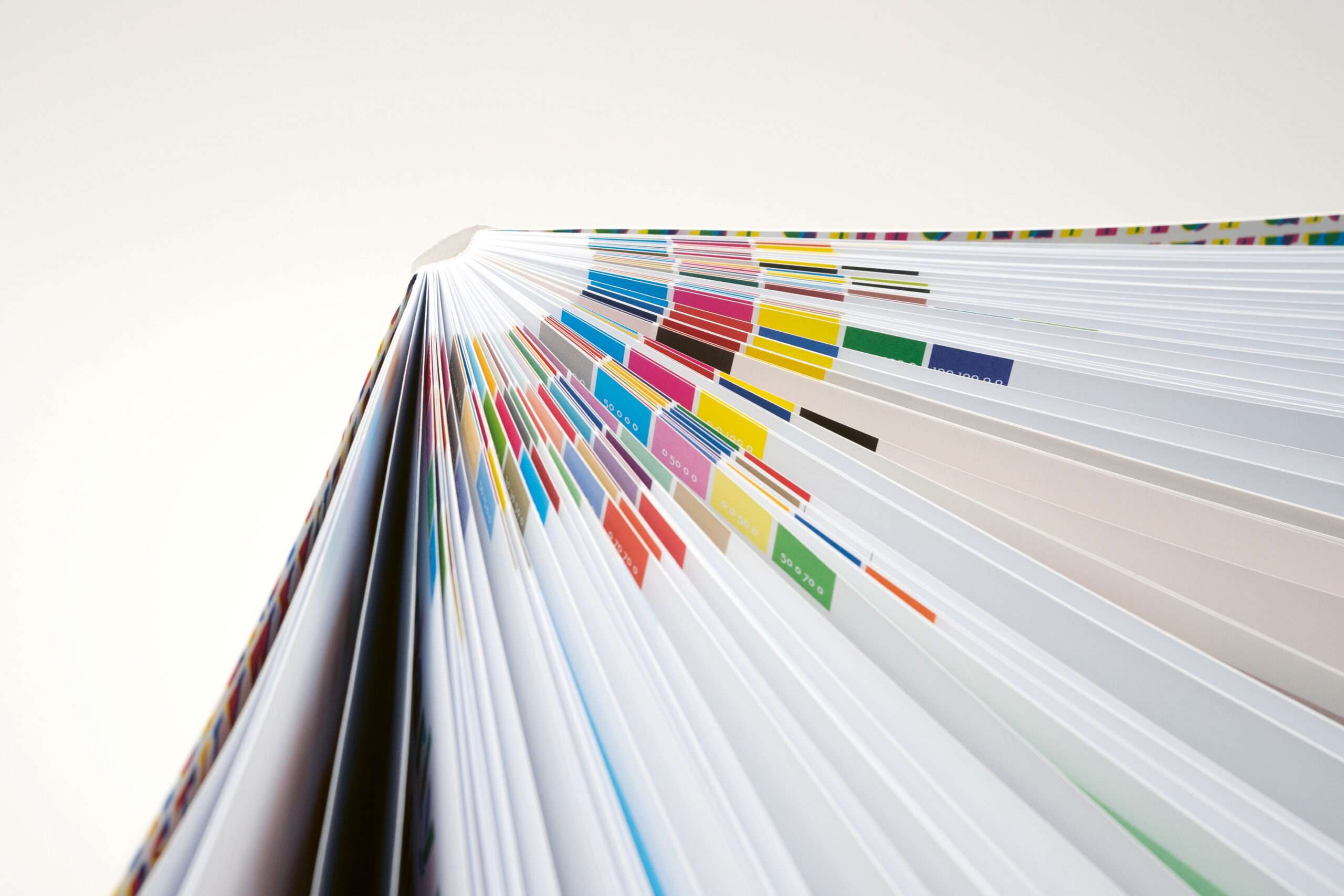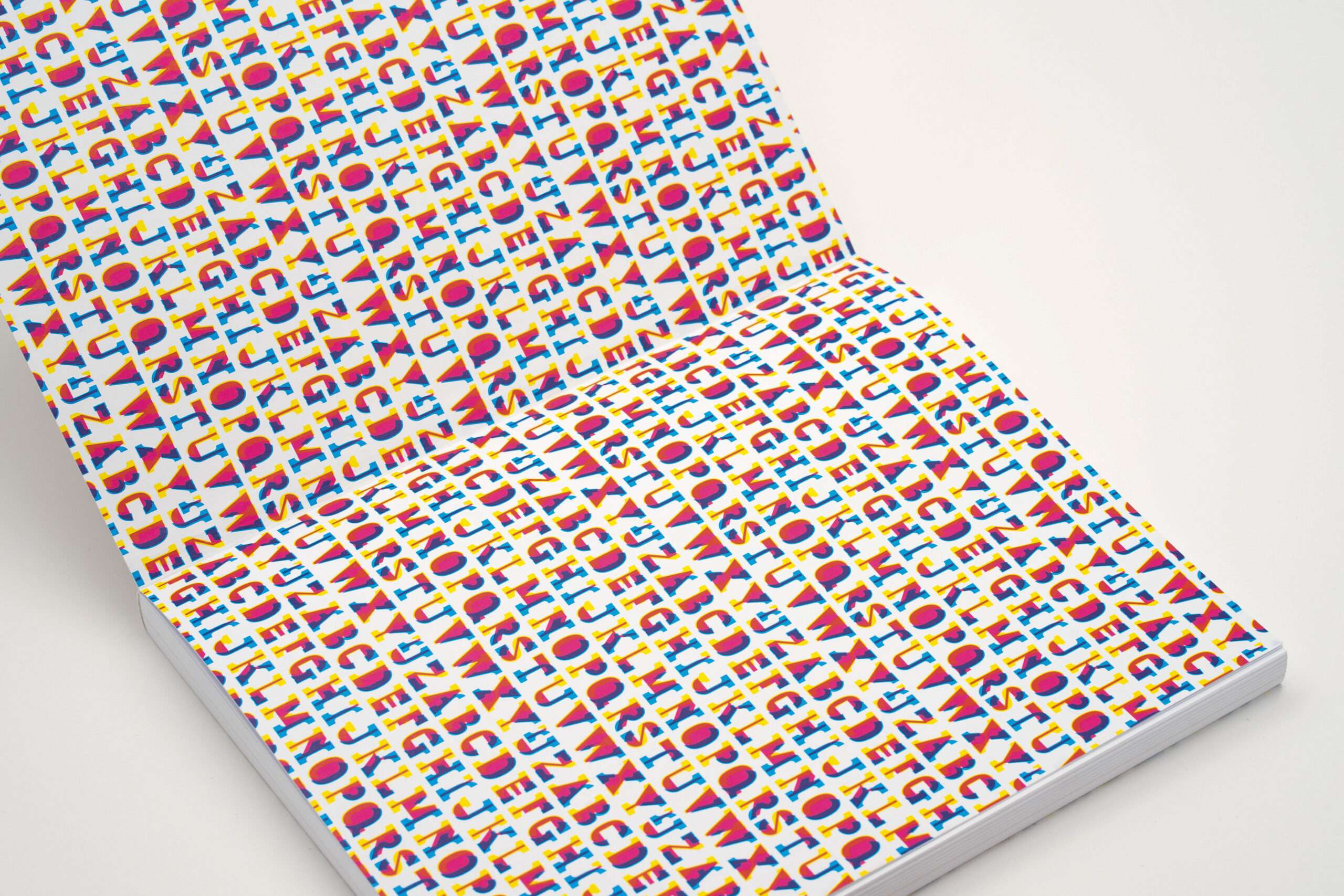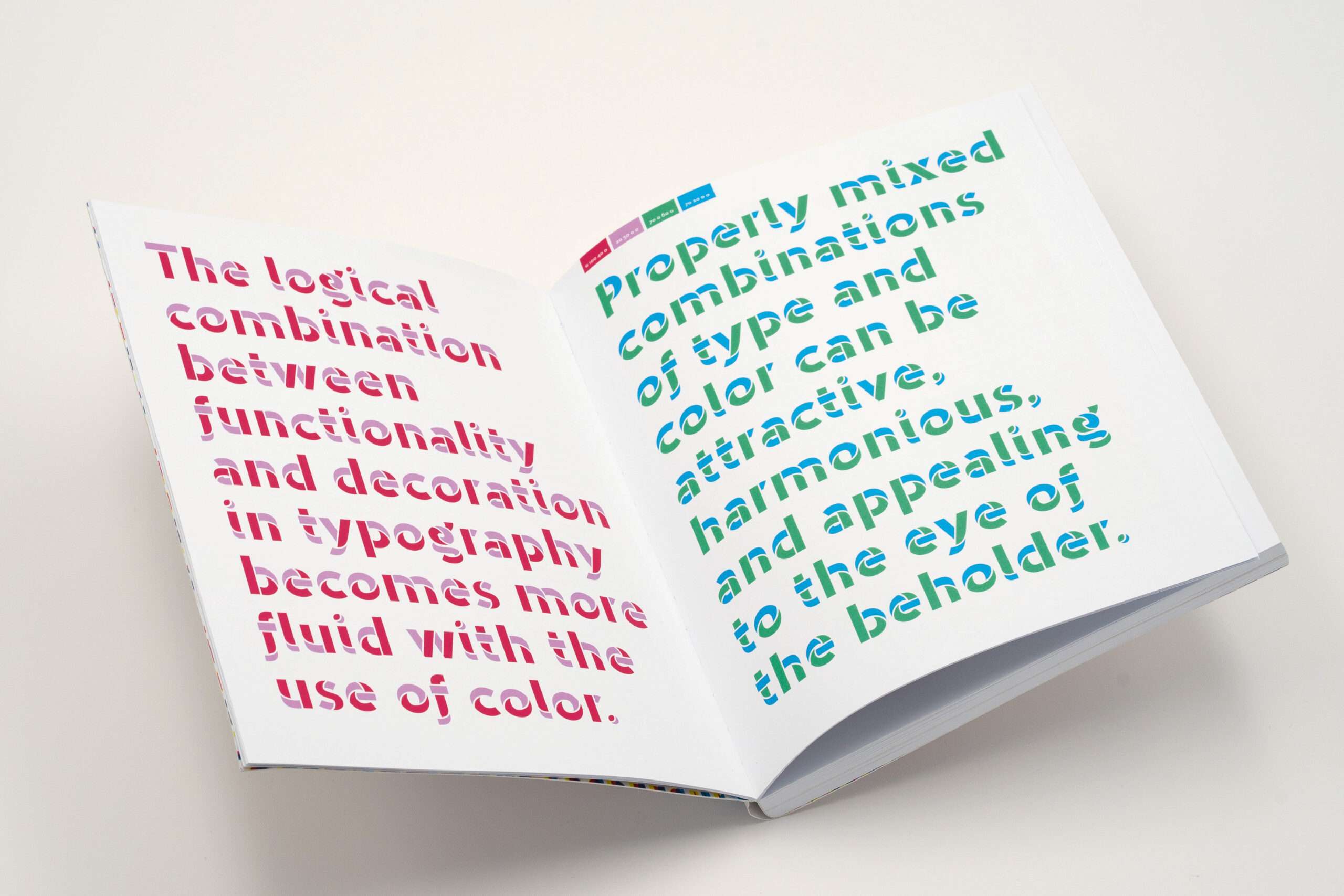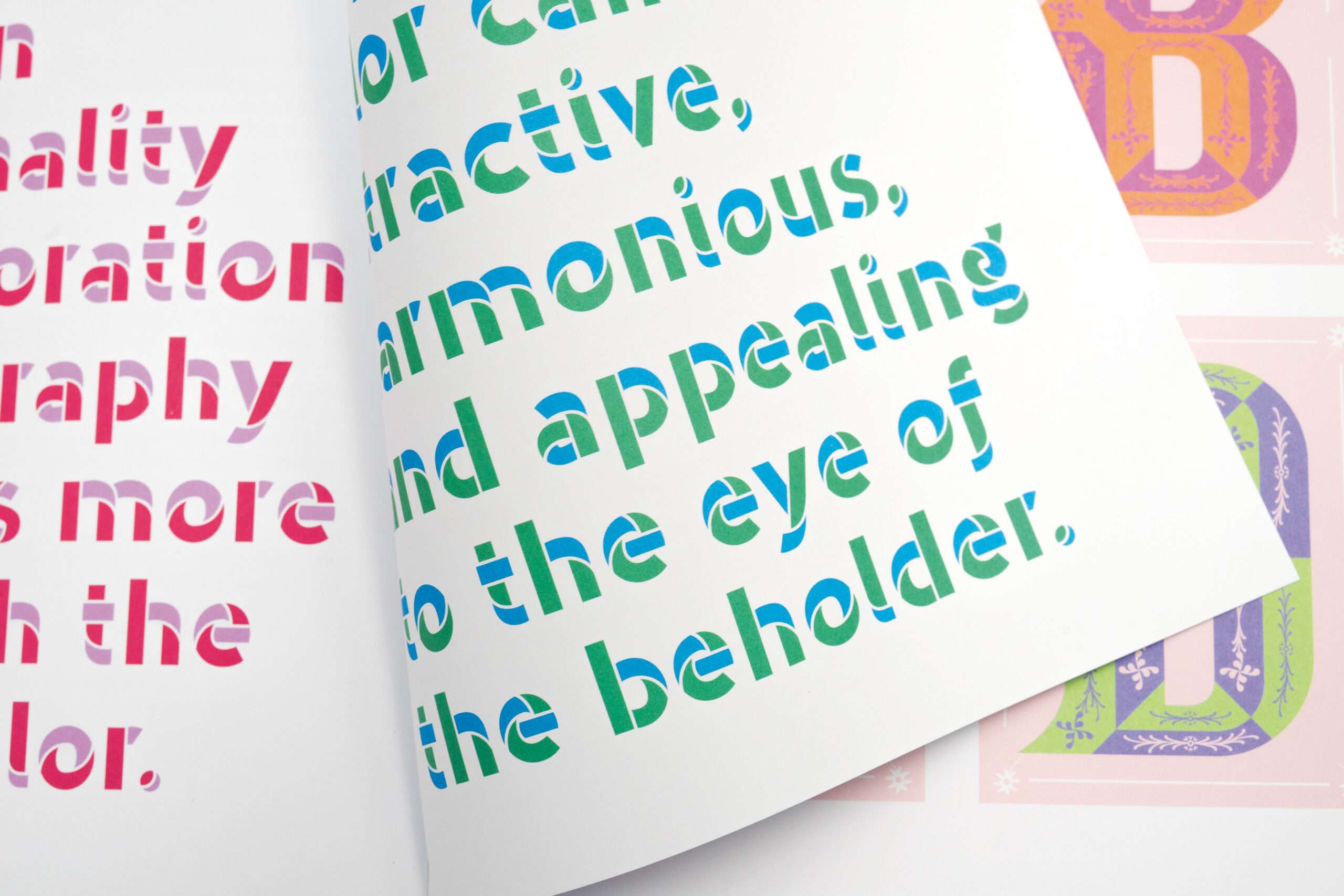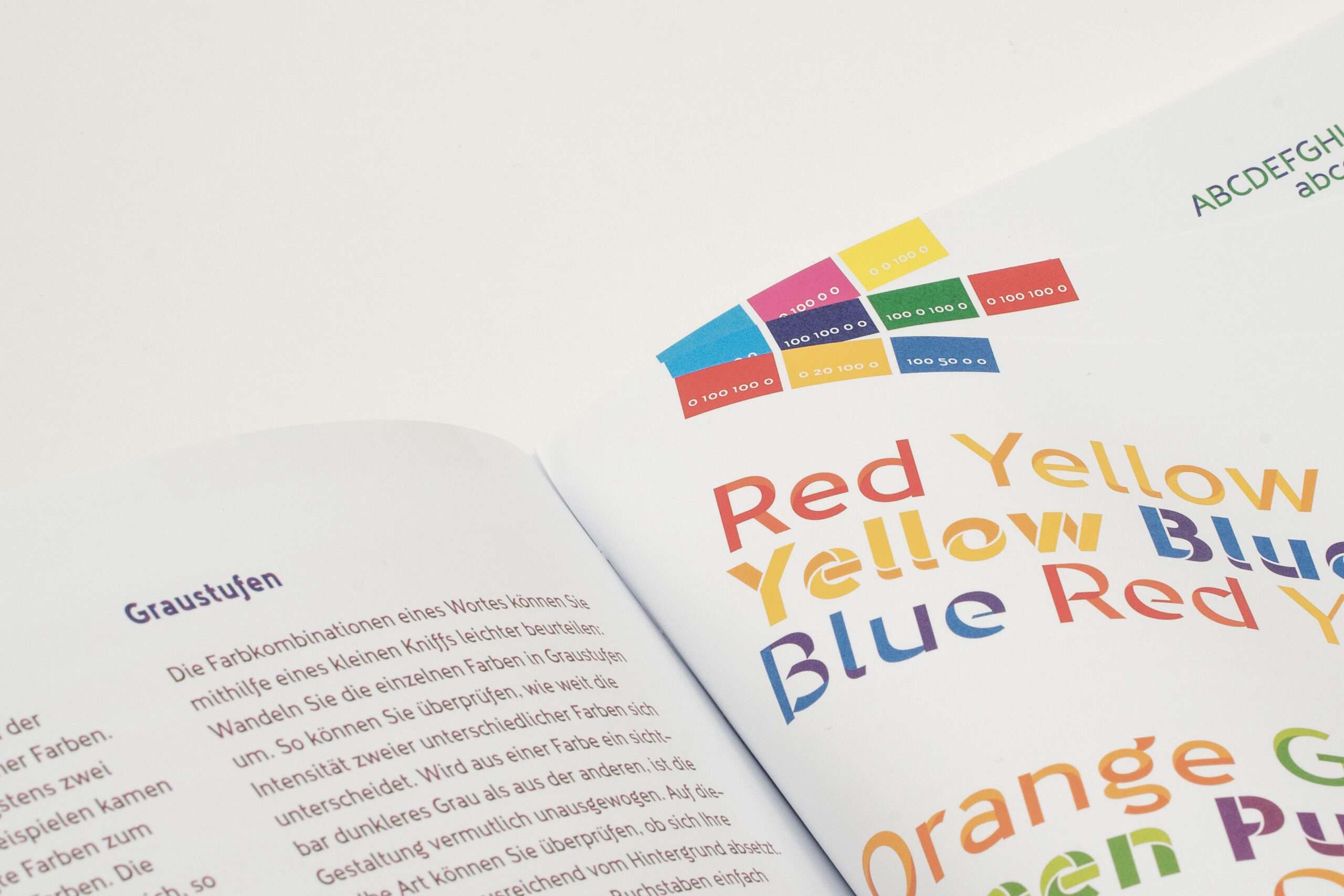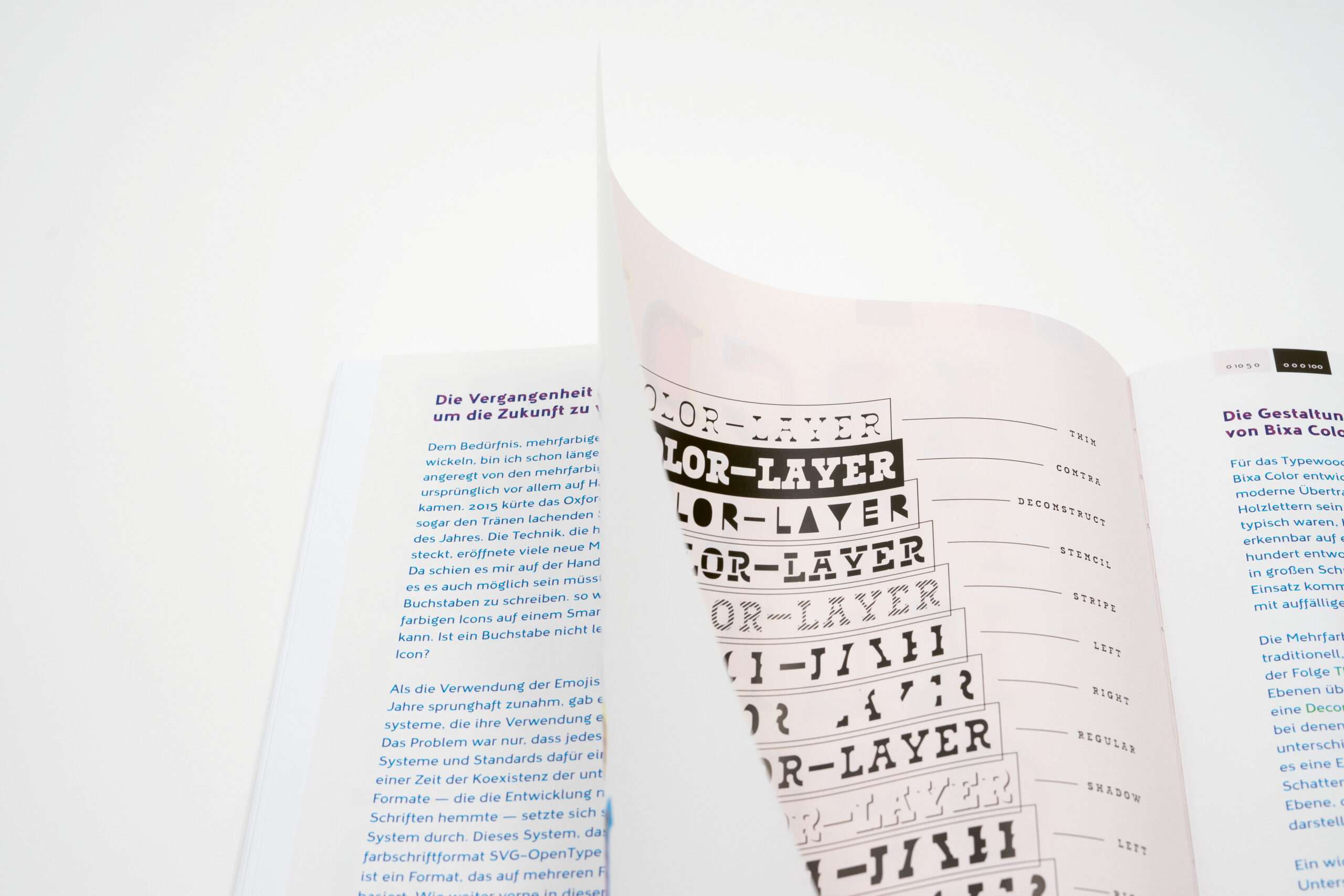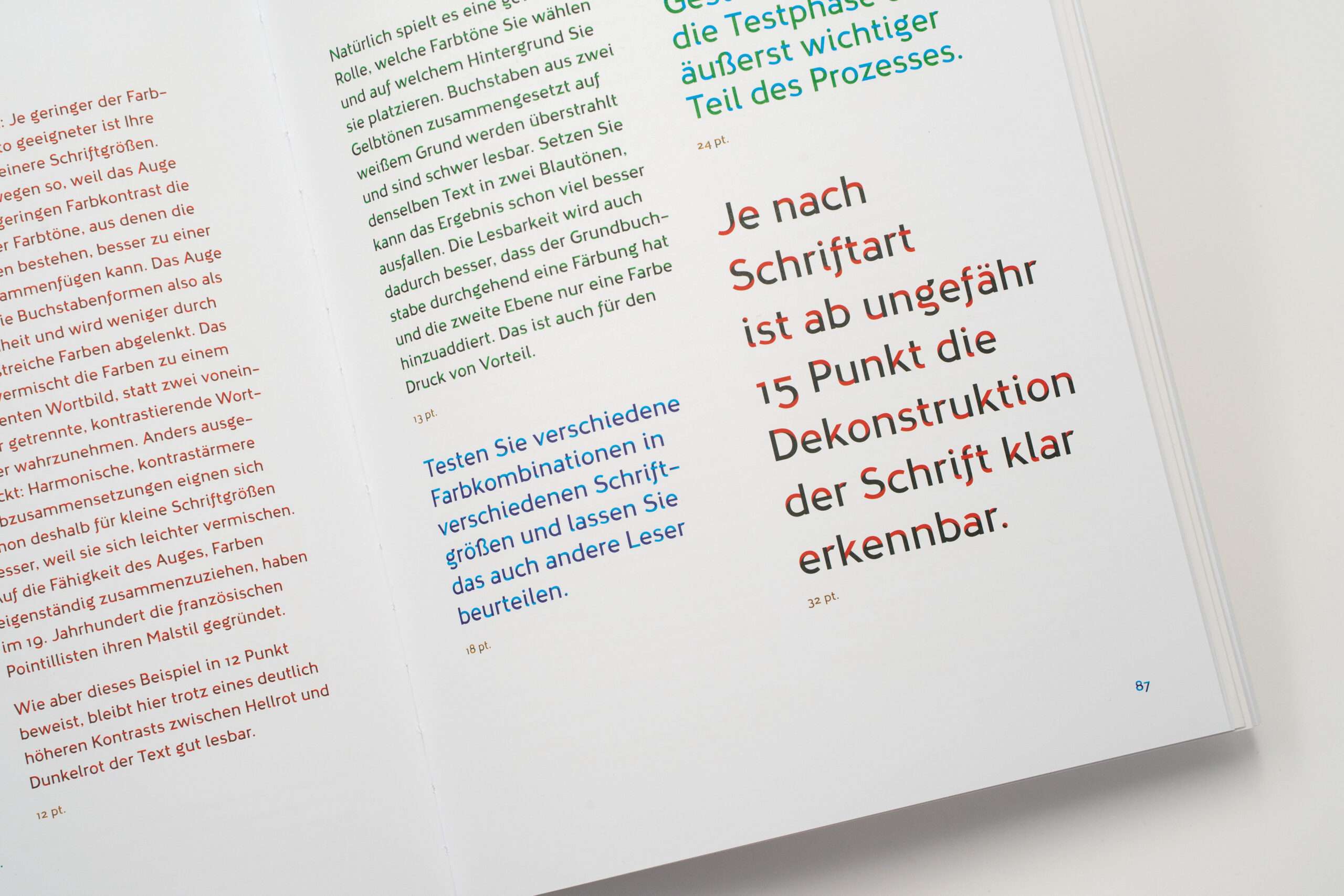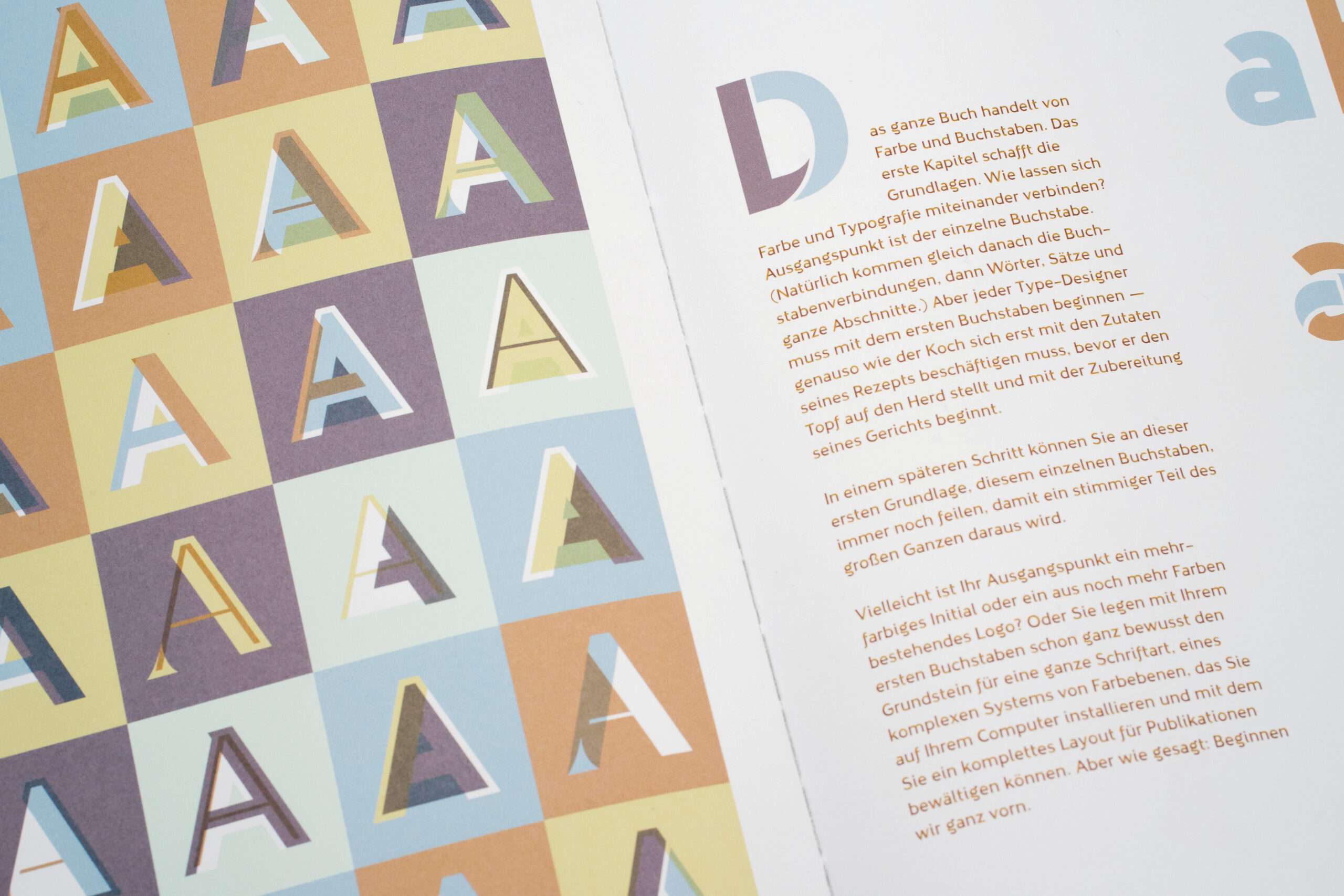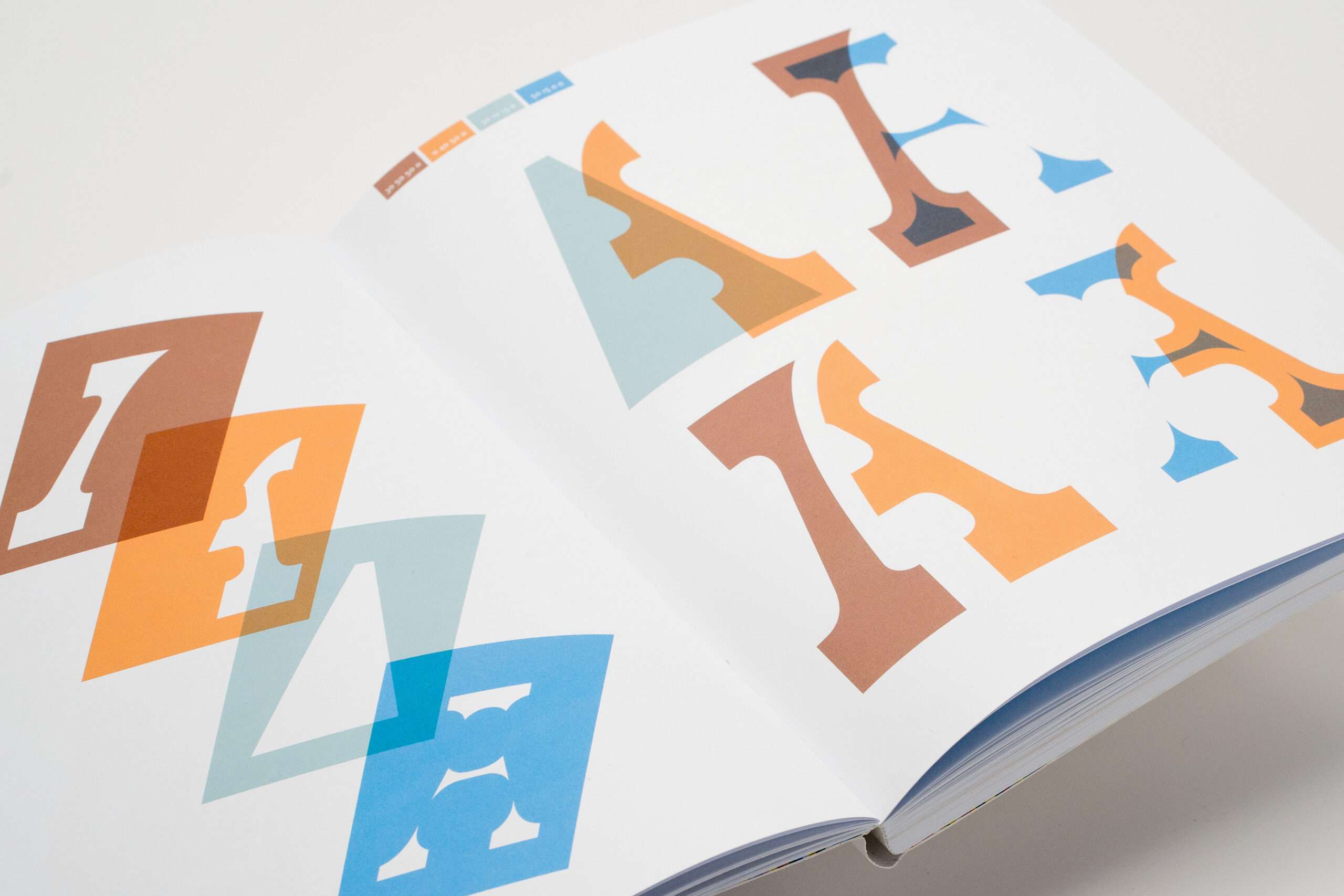
Die Zukunft der Typografie ist bunt!
Multicolored-Multi-Layer-Fonts – nie gehört? Seit einigen Jahren mischen mutige Schriftgestalter die »schwarze Kunst« mit mehrfarbigen Multi-Layer-Schriften auf. Multicolored Fonts bedienen sich einer Erweiterung des OpenType Formates und bringen Farbe ins Lesen.
Bislang ist das ein Insider-Trend. Nun aber legt Mark van Wageningen seine Forschungen zu mehrfarbigen Schriften vor. Systematisch untersucht er, wie Farbe und Schrift interagieren. Welche Kontraste wie wirken. Wie Mehrfarbigkeit, Form, Duktus und Lesbarkeit einander beeinflussen. Und ob das Ganze in kleinen Schriftgraden für Fließtext auch funktioniert.
In einem farbenfrohen Typo-Workshop vermittelt er das Know-how, das Sie brauchen, um mehrfarbige Schriften zu entwerfen und anzuwenden. Ihr Schlüssel zu vollkommen neuen Ausdrucksmöglichkeiten in der Gestaltung von Type, Typo und Text. Analog und digital. Gestalten Sie den neuen Mega-Trend mit!
Bunt ist das neue Schwarz!
Die Einsatzmöglichkeiten mehrfarbiger Schriften reichen von multicolored Logos und Corporate Fonts über Type-Animationen und anderen Webanwendungen bis zu interaktiven Farbspielen. Von Multicolor-Multilayer-Displayschriften bis zu regenbogenbunten Fließtexten. Farbe gibt der Gestaltung mit Text neue Ausdrucksmöglichkeiten.
Schrift farbig zu denken ist aber auch eine echte Herausforderung für Gestalter+innen:
Wie haucht man einer Schrift gekonnt Farbe ein? Wie bewahrt man sich davor, es zu bunt zu treiben? Was gilt es zu beachten, wenn man anstelle schwarzer (oder anders einfarbiger) mehrfarbige Schriften entwirft? Welche Hürden müssen Multicolorfonts im Hinblick auf Buchstabenform, Zurichtung, Farbkombination und Lesbarkeit nehmen?
Das erste Buch zu mehrfarbigen Multi-Layer-Schriften
All das verrät Mark van Wageningen farbenfroh und mit ansteckender Begeisterung in diesem Buch. Aufbauend auf Experimenten und Erfahrungen. Mit so viel Farblehre und Typo-Grundlagen wie nötig und so vielen Anregungen wie möglich. Werden Sie Farb-Font-Fan!
Das Holzlettern-Entwurfs-Experiment
Mark van Wageningen besann sich für den Entwurf seiner mehrfarbigen Multi-Layer-Schriften zurück auf den Druck mit Holzlettern. Mit den guten alten analogen Mitteln studierte er Form- und Farbkombinationen. Mit eigens für dieses typografische Experiment CNC-gefrästen Holzletternsets experimentierte er, bis er glaubte, die grundlegenden Regeln für den Entwurf mehrfarbiger Schriften gefunden zu haben. Eine Art Deklaration der Dekonstruktion des Typedesigns. Der nächste Schritt führte zurück an den Computer, zum Entwurf der variantenreichen Novo Typo Bixa und dem Novo Typo Book. Zwei Beweise für die Power of Color and Type, awarded for Typographic Excellence.
Der Typo-Virus
Dann lässt eine solche Eroberung ihn nicht mehr los. Er träumt nachts von mehrfarbigen Multi-Layer-Schriften und einem Buch dazu. Er telefoniert, er steckt an mit seiner Buch-Begeisterung. Und Mark van Wageningen beginnt zu schreiben. In babylonischer Sprachvielfalt und verbindender Typografie-Leidenschaft beginnt ein Ringen um den Inhalt des Buches. Die beiden treffen sich, Texte werden übersetzt, lektoriert, übersetzt, umgeschrieben. Jeder andere hätte dieses Experiment längst abgebrochen. Zu teuer. Zu aufwändig. Zu kompliziert. Für Mark von Wageningen und Bertram Schmidt-Friderichs gelten solche Argumente nicht. Sie geben Wochenenden dran und Nächte her, um Gestalter+innen-Leben bunter und facettenreicher zu machen. Mit dem ersten Buch zu mehrfarbigen Multi-Layer-Schriften, ihrem Entwurf und Einsatz. Im Analogen und im Digitalen. Denn in beiden Fällen gibt es einiges zu beachten!
Was gilt es beim Einsatz mehrfarbiger Multi-Layer-Schriften zu beachten?
Auch darauf geht Mark van Wageningen ein. Denn sowohl im analogen Druck als auch in Webanwendungen stellen mehrfarbige Multilayer-Schriften Ansprüche an Kreative und Techniker. Wenn auf Papier oder dem Bildschirm desjenigen, der Ihre Webanwendung öffnet, das zu sehen sein soll, was Sie gestaltet haben, gilt es einige Hürden zu nehmen. Dieses Buch verrät, welche.
Zu Ausstattung und Gestaltung
Color & Type
Mehrfarbige Multi-Layer-Schriften entwerfen und anwenden
Die Zukunft der Typografie … ist bunt